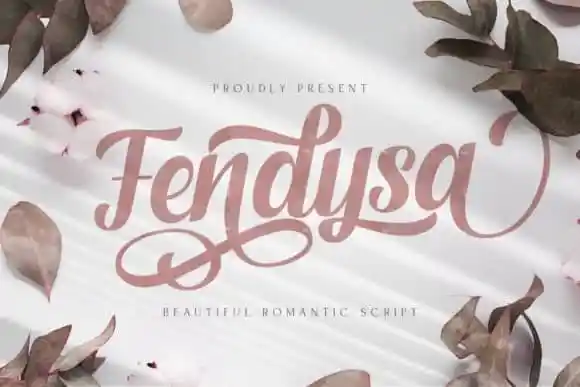
A Fendysa Calligraphy Font é uma nova criação cuidadosamente desenvolvida no formato de tipos de escrita script. Desenhada pela StringLabs e compartilhada pelo site 99designs, essa font se destaca por sua aparência alegre e descontraída, que faz dela uma opção ideal para projetos DIY ou redes sociais como o Instagram. O design é repleto de charmosas ondulações e ligações, tornando-a extremamente versátil, adaptável a diversos usos. Com apenas duas linhas, já se pode imaginar a Fendysa transformando qualquer projeto em uma verdadeira obra de arte. Seja para ilustrar seu blog com estilo ou para personalizar suas cartas e listras de Instagram, o uso desta font certamente adicionará um toque único e alegre ao design do seu trabalho.